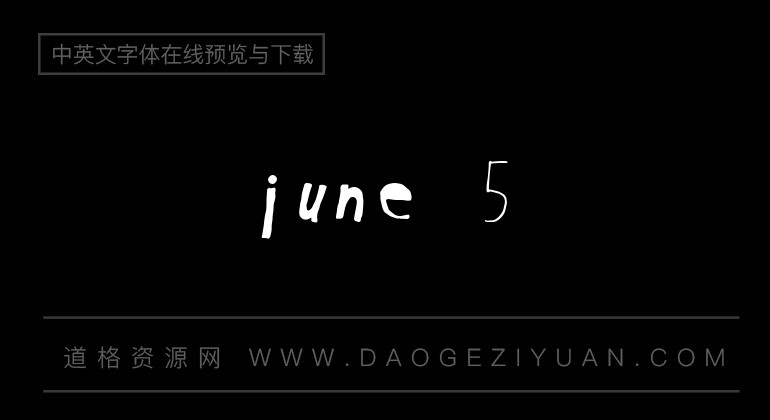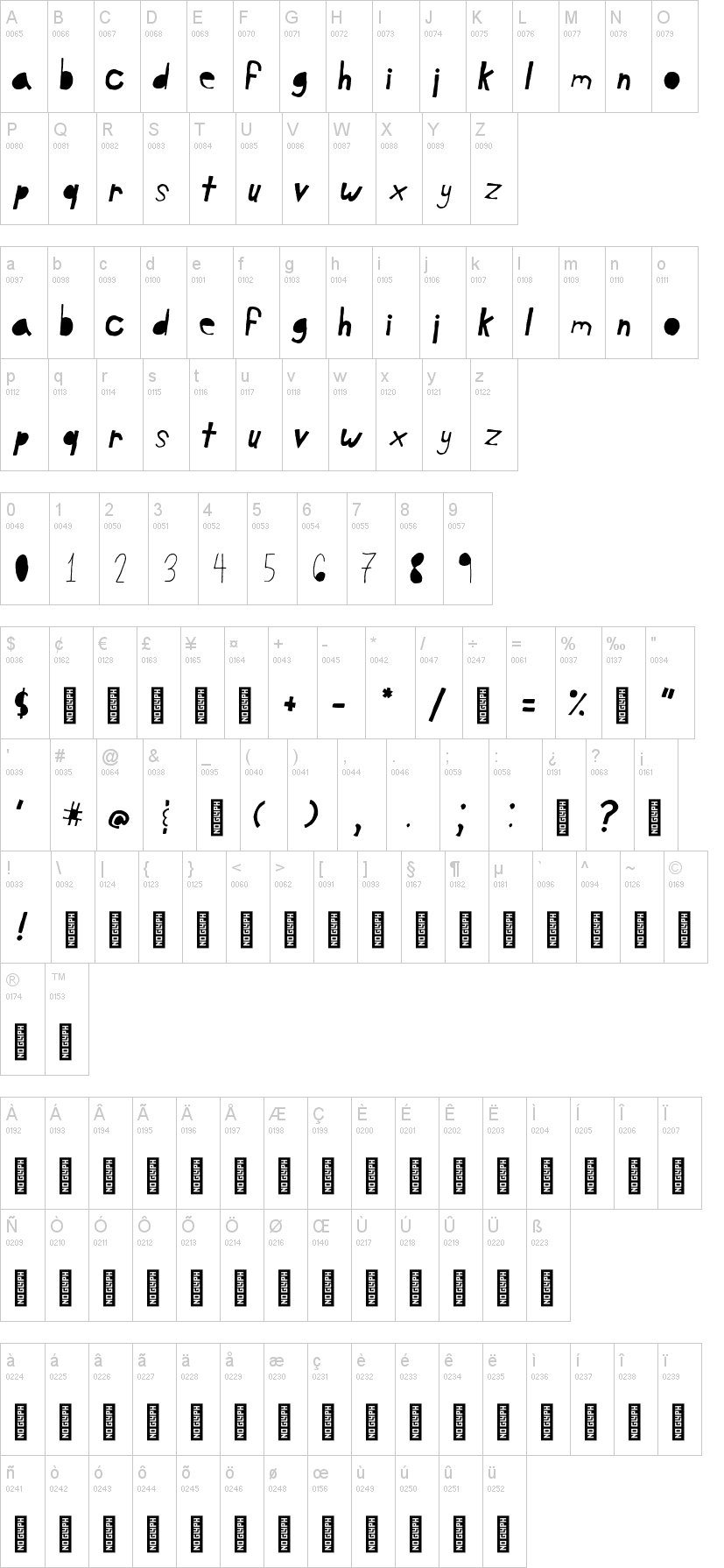
June 5 字体是一款由美国设计师米歇尔·布鲁克斯(Michelle Brucks)设计的英文字体,以清新的外观和优雅的笔画,极具现代感。字体灵感来源于20世纪50年代的经典美式报刊,具有明亮的色彩,优雅的笔画,清晰的字形,以及温暖的调调。June 5 字体既可以用于印刷,也可以用于网页设计,是一款多功能的字体。内容介绍
June 5是一款非常不错的手写艺术字体,具有很好的视觉感,适合于文化类的宣传设计、商业类品牌的广告和产品包装设计以及个性化文字排版等较多场景。